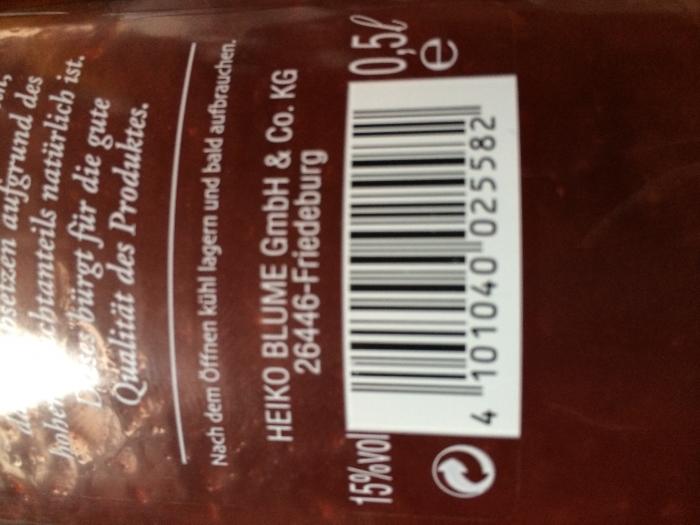
Welche Schriftart ist das? (15% vol)
ich habe hier eine Getränkeflasche und hätte gerne gewusst welche Schriftart ist die 15%vol   und 0,5l
Und wie bekomme ich die so eng ?
Sehr wahrscxheinlich die gleiche Schrift, mit der auch der Firmenname geschrieben wurde, und dann im Grafikprogramm, mit dewm das Etikett entworfen wurde gewaltsam zusamnmengestaucht. Gut möglich ists Arial. den sowas macht eigentlich nur eion Otto Arialverbraucher nach dem Genuß´des Flascheninhalts.